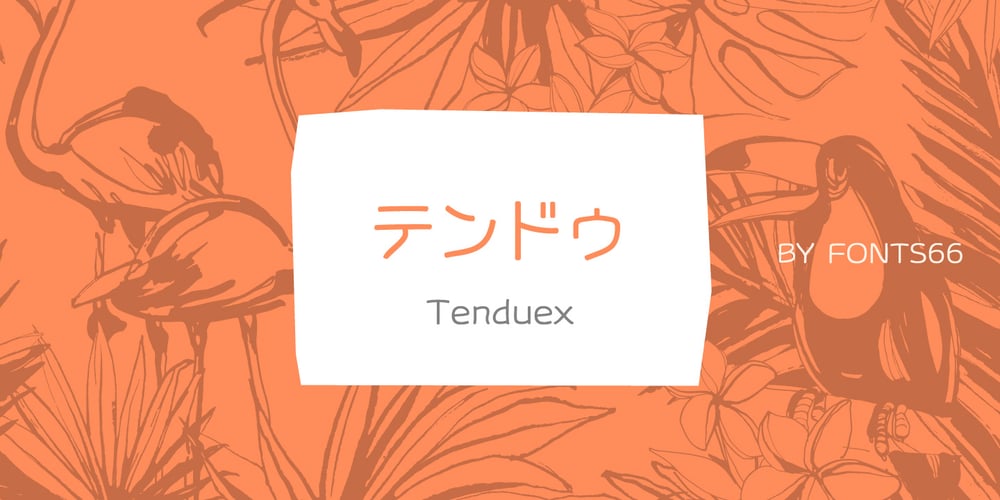
SF Tenduex Font Family was designed by published by Fonts66. SF Tenduex contains 4 styles and family package options. Historic font that has been used for seal for a long time in Japan. 現代の丸ゴシック体をみると、そのルーツは篆書に有るような気がします。筆で書かれているのも関わらず、エレメントのけ形状はほぼ丸ゴシック体に見えます。 しかし部首などの字体かなり異なり判読しにくい文字も見られます。 そこでユニークな字体を残しつつ、分かりやすき読みやすくしたフォントがテンドゥです。 文字のキャラクターは古いイメージを感じますので歴史的なもの(地名、寺社、旅館)の名称やその説明文などに適しています。 逆に真逆の表現に使っても面白いと思います。